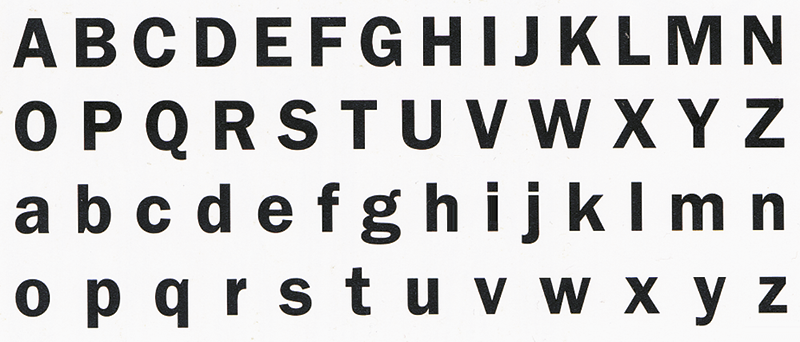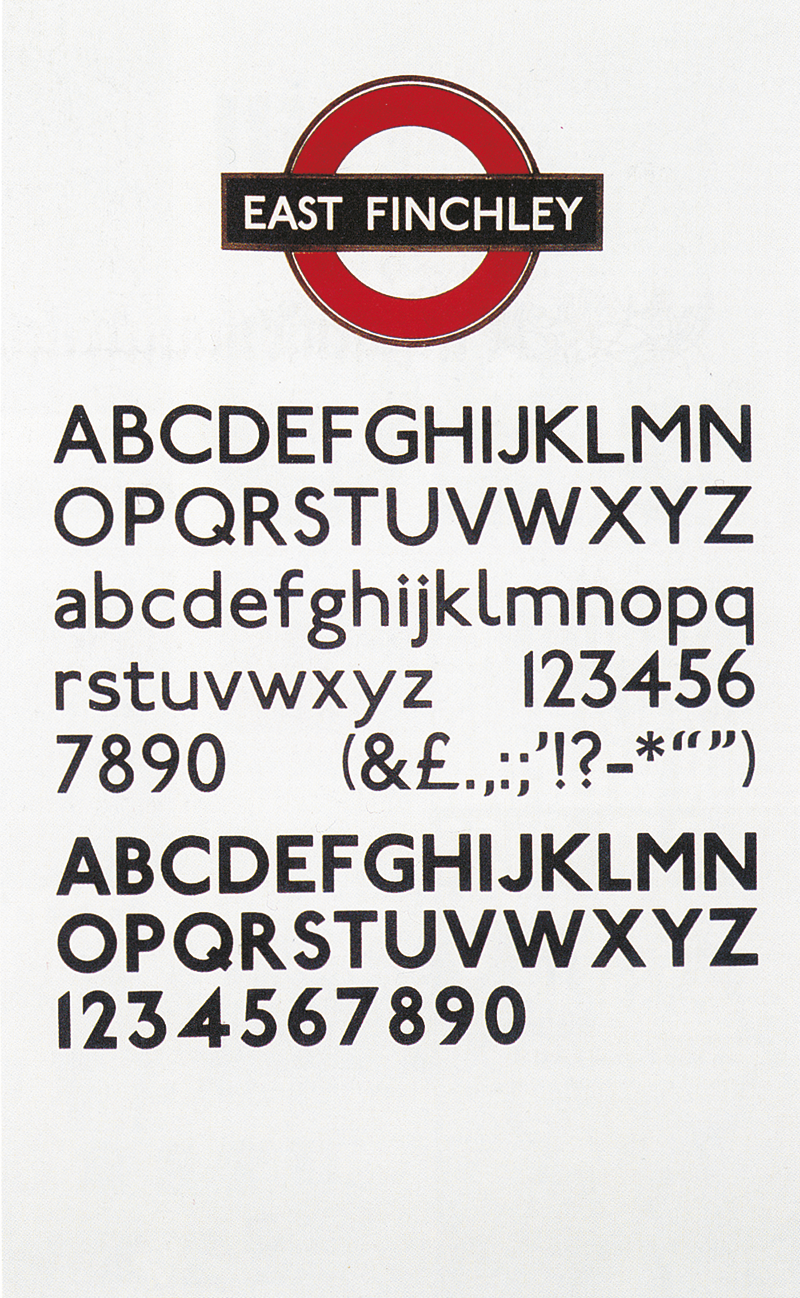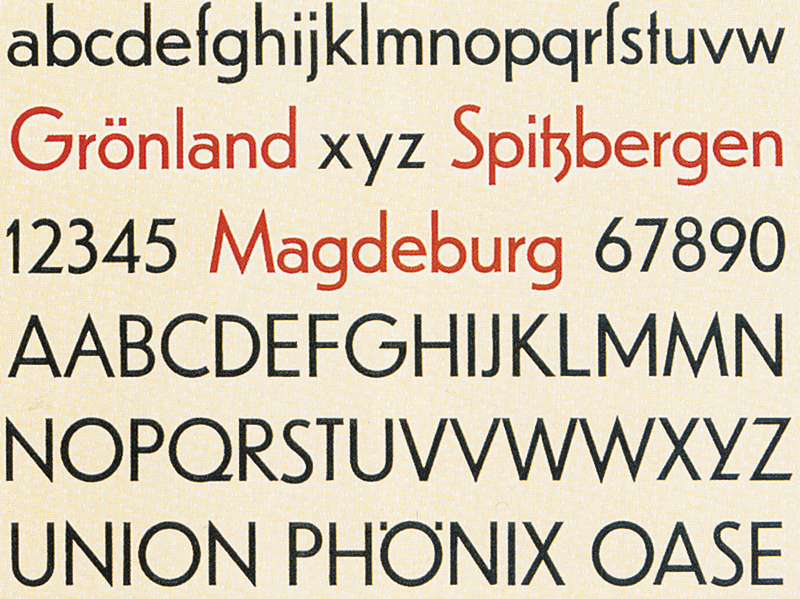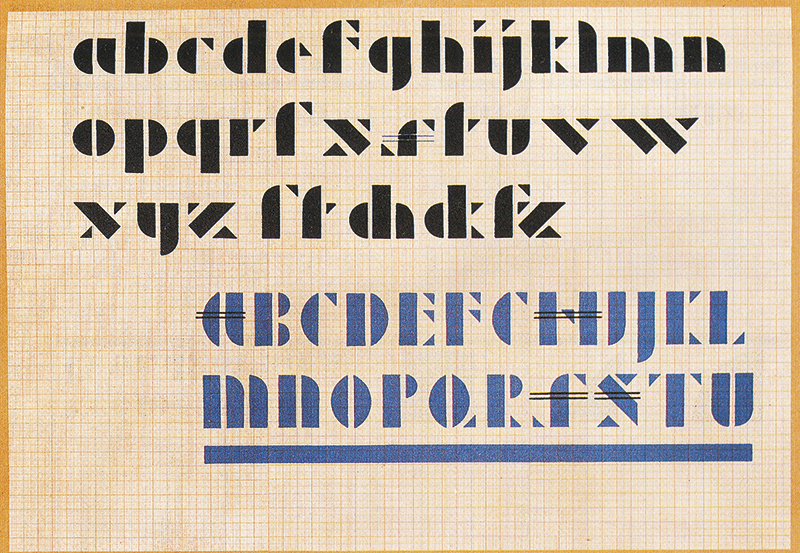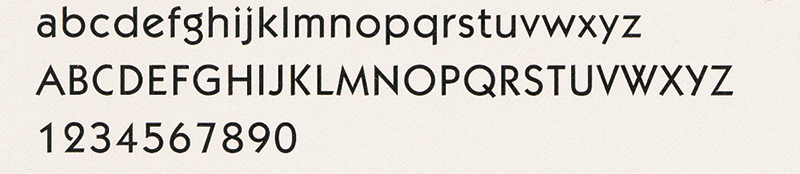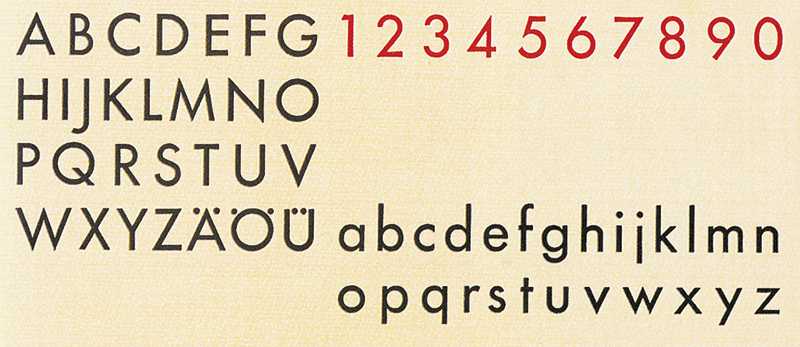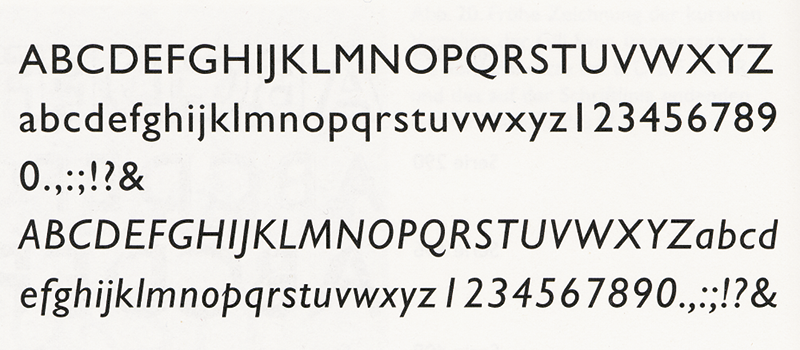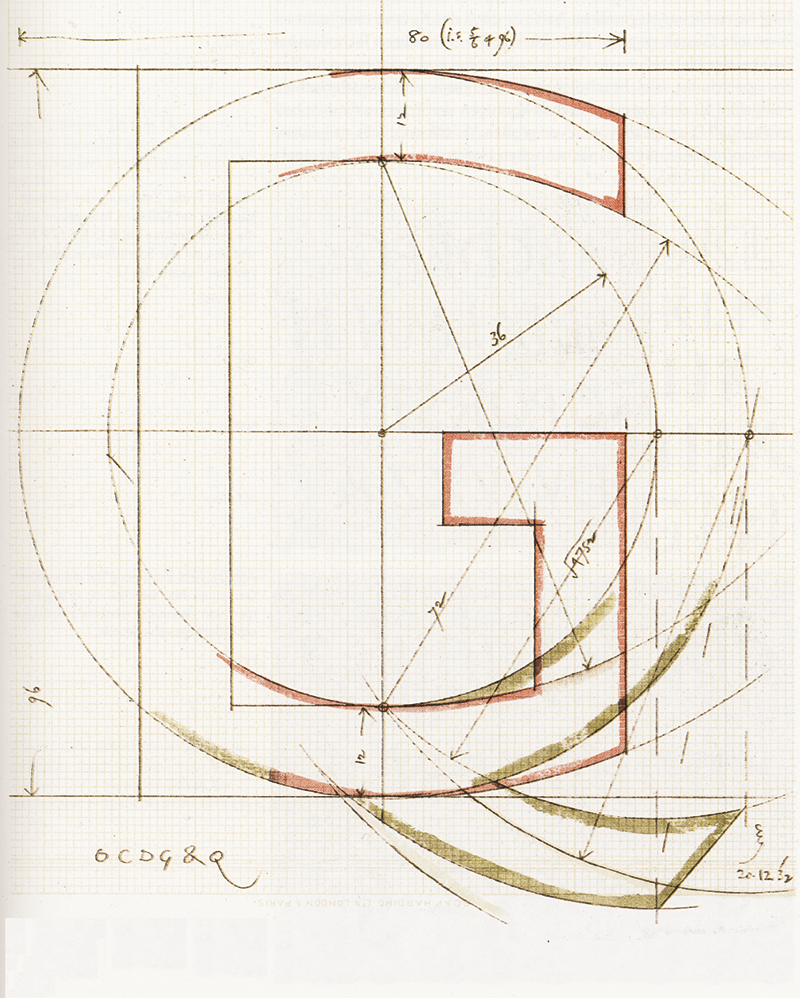
Exkurs: kurze Geschichte der Grotesk
Serifenlose Majuskelalphabete dokumentiert die Epigraphik in der Form der Auf- und Inschriften zur Zeit des Perikles (um 460–430 v. Chr.) in Athen und in der hellenistischen Epoche Ägyptens. Das berühmteste Epigraph ist der Rosetta-Stein mit seinen altgriechischen Majuskeln. William Caslon IV. hat 1816 erstmalig eine serifenlose Schrift entworfen und diese im Musterkatalog seiner Druckerei veröffentlicht. Anscheinend war er vom Erfolg dieser Schrift nicht besonders überzeugt, weil diese nur in Versalien und in der Größe von 28 Punkt existierte. Genannt wurde sie „English Egyptian“ wohl im Zusammenhang mit den damals in Ägypten stattfindenden altägyptischen Entdeckungen und dem Feldzug Napoleons in Ägypten. | |
Diese frühe Egyptian ist allerdings nicht mit der serifenbetonten Egyptienne von Vincent Figgins zu verwechseln, die in ihrer Frühphase (ab 1817) in England noch als „antique“ bezeichnet wurde. Die Serifenlose wurde vor allem als Anzeigen und Reklameschrift (Akzidenzen), aber auch in den Überschriften bzw. Titelblättern verwendet. Am Beginn des XIX. Jahrhunderts verwendeten sie zahlreiche Architekten, Kartographen und Schildermacher (Hausnummern). Wegen der Einfachheit der Konstruktion wurde die Schrift auch für das Gravieren von Schildern und das Einfräsen bzw. Gießen von Typenbezeichnungen an Maschinen bevorzugt verwendet. In diesem Zusammenhang „verdient“ die Serifenlose den Namen „Industrie-Schrift“. Einige Jahre später – 1832 – entwarf Vincent Figgins eine serifenlose Majuskelschrift mit drei Schriftgraden, die unter dem Namen Two-line Great Primer Sans-serif bekannt wurde. Erstmals wird der Serifenlosen das Prädikat „Sans-Serif“ (fr. „ohne Serif“) verliehen. Unter dieser Bezeichnung werden die Schriften im englischsprachigen Raum bis heute geführt. Im gleichen Jahr publizierte William Thorowgood (†1877) die erste serifenlose Werksatzschrift mit einem Majuskel- und Minuskelalphabet. Diese Schrift wurde unter der Schriftbezeichnung „Grotesque“ 44 bekannt. In Deutschland wurde die serifenlose Schrift von Anfang an Grotesk genannt, was widerspiegelt, wie man über diese neuen Formen dachte. Doch den Namen „Grotesk“ tragen diese Schriften im deutschsprachigen Raum bis heute. Zum weiteren Meilenstein in der Entwicklung der Serifenlosen zählt der Entwurf der „Royal-Grotesk“ von Ferdinand Theinhardt für die wissenschaftlichen Publikationen der „Königlich-Preußischen Akademie der Wissenschaften zu Berlin“ im Jahr 1880. Durch den Einsatz der serifenlosen Schrift in den Veröffentlichungen machte Theinhardt die Grotesk „salonfähig“. Nachdem Hermann Berthold im Jahr 1908 die Theinhardsche Schriftgießerei übernahm, hat er die Royal-Grotesk als „Akzidenz Grotesk mager“ in seinen Katalogen gelistet. Diese Schrift des Hauses Berthold gilt bis heute als „die Grotesk“ schlechthin. In den Vereinigten Staaten suchte der Firmenverband American Type Founders (ATF) ebenfalls nach einer serifenlosen Schrift, die als Ausdruck der Moderne und Abkehr von der traditionellen Entwicklung dienen sollte. Im Lauf des XIX. Jahrhunderts kamen in dem Musterbuch der Foundry etwa 50 Schnitte charakterloser Gothic von extraschmal zu extrabreit vor. |
Der Chefentwerfer von ATF Morris Fuller Benton wollte neue Impulse setzen und entwickelte 1902 die Franklin Gothic, die einen Kontrast zu den bekannten Akzidenzschriften bildet. Details wie das Dünnerwerden der Striche dort, wo Rundungen in den Stamm einlaufen, verleihen dem Schriftbild ein Leben, durch das es sich von anderen serifenlosen Fettschriften abhebt (Blackwell, 2004: 25). Die Nachfrage der Druckereien nach den neuen Schriften war groß – aus diesem Grund entstanden im Haus ATF zwei weitere Gothic Familien: die Alternate Gothic (1903) und die News Gothic (1908). |
In England wandten sich 1913 zwei Mitarbeiter der London Transport Board an die Schriftsachverständigen Edward Johnston und Eric Gill um die Möglichkeit der Schaffung einer leicht leserlichen, optimal erfassbaren Schrift für die Untergrundbahn zu erörtern. Da Gill sich an dem Projekt nicht beteiligen konnte, begann Johnston 1915 allein die Arbeit an den Entwürfen. Während der Arbeit tauschten sie ihre Meinungen aus – die Beiden verband ein freundschaftliches Verhältnis; nach Abschluss des Auftrags erhielt Gill sogar einen Honoraranteil von 10% für seine Beratertätigkeit. Die neu entstandene Schrift basierte auf den Proportionen der römischen Kapitalis der Trajanssäule und bestand aus Versalien und Gemeinen. Die Johnston Grotesk wurde in den 1980er Jahren im Auftrag von London Transport von der Firma Banks & Miles als New Johnston neu aufgelegt und revidiert. Johnstons Alphabete von 1916 unterschieden sich erheblich von den aus der zweiten Hälfte des vorletzten Jahrhunderts stammenden Serifenlosen; sie waren geradezu revolutionär und besaßen eine völlig neue Qualität. Eric Gill sprach sogar von korrupten Formen der früheren Serifenlosen (Caflisch, 2004: Bd. 2, 8). |
Nach dem I. Weltkrieg beeinflussten Konstruktivismus, Dadaismus, Futurismus und die informative Sachlichkeit als künstlerische Strömungen viele Maler, Architekten und auch Typographen in ganz Europa. Besonders in Deutschland manifestierten sich die Stile in den Erzeugnissen der Kunstgewerbeschule Bauhaus. In der Grotesk sahen die Künstler die adäquate Schrift der Moderne. Aus dem Gedankengut entstanden die wegweisenden Groteskschriften: 1922 die Erbar-Grotesk von Jakob Erbar (Köln), 1925 Albers von Josef Albers (Lehrer am Bauhaus), ebenfalls 1925 Bayer von Herbert Bayer (Leiter der Abteilung für Typographie am Bauhaus), 1927 die aus den Elementen Kreis und Gerade bestehende Futura von Paul Renner und ebenfalls 1927 die von Rudolf Koch für die Offenbacher Schriftgießerei Gebrüder Klingspor entworfene Kabel. Während dessen erlangte in England der Schüler Johnstons Eric Gill, von Beruf Bildhauer, in typographischen Kreisen großen Ruhm. Er selbst verstand es wie kaum ein anderer, die im Stein gehauenen Schriften souverän zu entwerfen, aber auch die Problematik der altrömischen Epigraphe nachvollziehen zu können. Seine zeitlosen Schriftentwürfe, die bis heute an Eleganz und Selbständigkeit nichts eingebüßt haben, wurden durch die Kenner enthusiastisch gefeiert. Aus seiner Hand stammen Perpetua (1925–36), Gill Sans (1926–1939), Monotype Solus (1928–29), Golden Cockerel Type (1925–29), Joanna (1929–1937), Aries (1932), Bunyan (1934) und Jubilee (1933–34). Die Gill Sans als einzige Groteskschrift unter den oben genannten zeigt, wie behutsam und umsichtig Gill bei den Entwürfen ans Werk ging. Zur Entwicklung dieser Schrift motivierte Gill auch Stanley Morrison, um den „in Mode gekommenen deutschen geometrisierten Schriften ein Konkurrenzprodukt der Monotype entgegenstellen zu können“ (Caflisch, 2004: Bd. 2, 31). |
Einer der größten Typographie-Theoretiker des XX. Jahrhunderts im deutschen Sprachraum Jan Tschichold entwarf 1926 ebenfalls ein „alfabet“ und leistete seinen Beitrag zu der Diskussion um die „Elementare Typographie“. Die Position Tschicholds bezüglich der Groteskschrift änderte sich im Lauf seiner Vortragstätigkeit einige Male. Als enthusiastischer Vertreter der „Elementaren Typographie“ hielt er 1925 fest: Elementare Schriftform ist die Groteskschrift aller Variationen: mager – halbfett – fett – schmal bis breit. (…) Die Mediäval-Antiqua ist die der heute Lebenden geläufigste Form der Druckschrift. Im (fortlaufenden) Werksatz besitzt sie heute noch, ohne eigentlich elementar gestaltet zu sein, vor vielen Groteskschriften den Vorzug besserer Lesbarkeit. Solange noch keine, auch im Werksatz gut lesbare elementare Form geschaffen ist, ist zweckmäßig eine unpersönliche, sachliche, möglichst wenig aufdringliche Form der Mediäval-Antiqua (also eine solche, in der ein zeitlicher oder persönlicher Charakter möglichst wenig zum Ausdruck kommt) der Grotesk vorzuziehen. Eine außerordentliche Ersparnis würde durch die ausschließliche Verwendung des kleinen Alphabets unter Ausschaltung aller Großbuchstaben erreicht, eine Schreibweise, die von allen Neuerern der Schrift als unsre Zukunftsschrift empfohlen wird (Tschichold, Elementare Typographie, 1991: Bd. 1, 14f).
So führt die Grotesk ihren historischen Namen mit vollem Recht. Sie ist ein eigentliches Monstrum. Die Erwählung der stilistisch ins neunzehnte Jahrhundert gehörigen Grotesk zur alleinseligmachenden Form offenbart die Unfruchtbarkeit ihrer Anhänger in Schriftdingen. Mit einer schwachen und erfolglosen Ausnahme hat keiner dieser Bauhausleute, die auf anderen Gebieten so schöpferisch gewesen sind und sich so sehr zeitgemäß fühlen, je eine neue Druckschrift hervorgebracht: Immer hat man sich mit älteren Typen, wenn auch nur mit den schlechtesten, begnügt. Von der besten zeitgenössischen Endstrichlosen, der Gill Sans Serif, wollen die Groteskanhänger nichts wissen, vielleicht weil diese nicht auf den entarteten Groteskschriften des neunzehnten Jahrhunderts fußt, die sie für unentbehrlich halten, sondern aus der Grundform unserer Schrift, der Antiqua der Renaissance, abgeleitet ist, offensichtlich einem roten Tuch für die Stiere des sogenannten Stiles unserer Zeit (Tschichold, Zur Typographie, 1991: Bd. 2, 258). In dieser Äußerung erkennt man einerseits die eindeutige Position für die klassischen Schriften, die antiquabasierend entwickelt werden sollen, andererseits die Anerkennung der Leistung Gills, der seine Schrift nicht geometrisch und konstruktivistisch, sondern von der Kalligraphie abgeleitet und nach den Majuskeln der Trajanssäule sehr behutsam entworfen hat. Erst einige Jahre später – 1970 – erläuterte Tschichold seine Position: Seit 1925 gab es die neue Typographie. Sie bekümmerte sich so gut wie gar nicht um das Buch, sondern um alle anderen Drucksachen. Hier konnte die Situation nicht schlimmer sein als sie war. Noch die Typographie um 1895 war viel besser als die der Inserate um 1925. Dies alles widerte mich derartig an, dass ich eine Umwälzung beschloß. Sie gelang mir sogar, dem Dreiundzwanzigjährigen! Anstelle der Unzahl fast hässlicher Schriftschnitte verlangte ich 1925, nur eine einzige Schriftart solle benützt werden, die Grotesk und als Formprinzip die Asymmetrie (ein ungenaues Wort für nichtzentrierten Satz). Damit schüttete ich zwar das Kind mit dem Bade aus, doch waren die Folgen zunächst heilsam. Die hässlichen Schriften und die dummen Ornamente verschwanden. Richtig wäre gewesen, zuerst nach guten Schriftschnitten zu suchen und diese verbreiten zu helfen. Meine damaligen Gedankenfolge ‚Welche ist die beste Schrift? Die einfachste Schrift. Welches ist die einfachste Schrift? Die Grotesk. Also ist die Grotesk die beste Schrift‘ ist ein Trugschluß. Die leserlichste Schrift ist die beste. (…) Wie konnte ich nur so naiv sein, nur die Grotesk gelten zu lassen! (Tschichold, Flöhe, 1991: Bd. 2, 360f.). |
Der II. Weltkrieg samt den Verboten der
Nationalsozialisten bezüglich der
„Entarteten Kunst“ und der
Fraktur als „Schwabacher
Judenletter“, sowie dem Die führenden Typographen verließen Deutschland. Als neue Zentren der Typographie etablierten sich in der Schweiz Zürich und Basel und in den USA Chicago und New York. Nach dem II. Weltkrieg erholte sich die typographische Szene nur langsam. Die neuen Entwürfe waren meist Revitalisierungen der alten Schriften. So geht beispielsweise die Folio (1957) von Konrad F. Bauer und Walter Baum auf die Breite Grotesk aus dem Jahr 1867 zurück. Die bis heute mit ungebrochener Popularität verwendete Helvetica (1958) von Max Miedinger hat ihre Wurzeln in der Schelter Grotesk der Leipziger Schriftgießerei Schelter & Giesecke aus dem Jahr 1880. |
Zu den bedeutendsten Serifenlosen des vergangenen Jahrhunderts zählen zweifellos die Univers und die Frutiger entworfen von Adrian Frutiger. Die Univers entstand in den Jahren 1954–57 für Deberny & Peignot. Mit ihr startete Frutiger den einzigartigen Versuch der Neuklassifizierung der Schnitte dieser Schriftfamilie: er verwendete nicht mehr die Begriffe „mager“, „fett“ oder „normal“, sondern ordnete den Schnitten Zahlen zu. In der Mitte steht Univers 55; die vertikale Achse bestimmt die Strichstärke, während in der Horizontalen sich Laufweite und Dickte verändern. Die Schriftschnitte mit den geraden Nummern sind kursiv. Wenn auch das System sich nur auf die Schriften von Frutiger beschränkt und sehr wenige Nachahmer gefunden hat, so wurde die Univers zu einer der weltweit dominierenden Druckschriften überhaupt. Im Jahr 1997 wurde sie von Frutiger neu aufgelegt und hat jetzt 59 Schnitte, kategorisiert mit Hilfe von drei Ziffern. Die „Normal“ hat nun die Nummer 430. Die erste Ziffer bezeichnet die Fette, die zweite die Weite, die dritte unterscheidet den normalen Schnitt (0) vom Kursiven (1). Frutiger wurde in den Jahren 1973–76 für das Leitsystem des Pariser Flughafens Charles de Gaulle entworfen und leitet sich von der Univers ab, ist jedoch offener. Mit kleinen Versalien und langen Ober- und Unterlängen der Gemeinen. Die Inspiration für Frutigers Entwurf waren eher die Antiqua-Schriften als die geometrisch konstruierten Serifenlosen. Im Jahr 2000 digitalisierte Frutiger für Linotype die Schriftfamilie Frutiger Next, die harmonischere Breiten vor allem bei den Kursiven kennzeichnet. Im digitalen Zeitalter entstanden zahlreiche, teilweise hochqualitative Groteskschriften, einige davon wurden speziell für die Arbeit am Bildschirm entwickelt. Im Gegensatz zu den Serifenschriften, die durch den Einsatz der Pixeldarstellung am Monitor sehr schnell „verwischen“, eignen sich die Serifenlose samt der Clear Type (oder XSF) Technologie bestens für die Bildschirmdarstellung. Diese modernen Digitalschriften auch nur aufzuzählen, würde jedoch den Rahmen dieses Exkurses sprengen. |
44 Der Begriff stammt vom Lateinischen „grotta“ und bedeutet Höhle im Berg oder unter der Erde bzw. ein unterirdischer Teil eines Gebäudes. Als man bei der Freilegung der Wandmalereien in den Ruinen des Goldenen Hauses des Kaisers Nero in Rom die phantastischen Kombinationen aus Menschen- Tier- und Pflanzenmotiven entdeckte, bezeichnete man sie als „grottesche“. Aus diesem Wort entstand das italienische „grottesco“ für merkwürdige, phantastische, lächerliche Malerei.